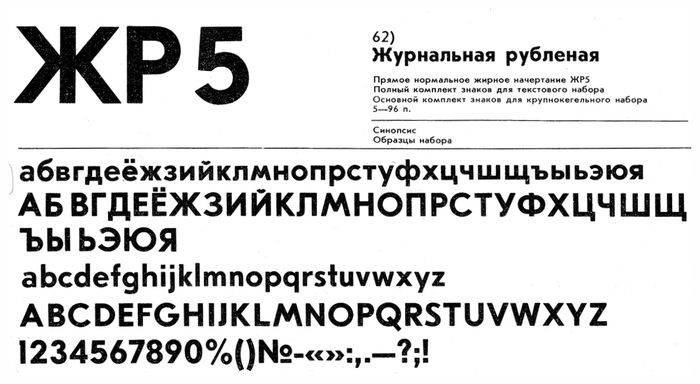
Какие выбрать шрифты для букваря и чем руководствоваться?
Сергей! Тут всё зависит от задачи и от вёрстки. На какой возраст рассчитан букварь? Как много текста будет на развороте? Какие будут иллюстрации? |
До сих пор существуют различные госты оформления детской литературы. В них, например, сказано, что антиквенные шрифты можно использовать только в литературе для детей от 11 лет. В букварях гост требует использования рубленых шрифтов, то есть без засечек. Эти стандарты существуют ещё с советских времён, и их целесообразность вызывает вопросы. Однако они до сих пор важны для некоторых издательств. Если от вас не требуют полного соответствия гостам, я бы не советовала опираться на них. Самый известный рубленый шрифт в советской детской литературе — гарнитура Букварная. Ей набирались буквари: Букварь. Просвещение, 1978 |
ОСТ 29.127-2002 оформления детской литературы |
На основе гарнитуры Букварной создан шрифт «Текстбук», а в 2008 году вышло обновление «Текстбук Нью». Несмотря на появление шрифтов-конкурентов, «Текстбук» не перестал быть популярен, и его до сих пор используют в детской литературе и не только. Например, Яндекс использовал этот шрифт для рекламных коммуникаций около пятнадцати лет. Самая узнаваемая фраза Яндекса, набранная этим шрифтом: Найдётся всё. Наружная реклама Яндекса, 2008 Я вижу главную проблему букварей не столько в выборе конкретного шрифта, сколько в общем облике книги. К сожалению, сейчас наиболее популярны такие буквари: Мария Манакова. Или даже такие: Марина Дружинина. Забавная азбука. Эксмо, 2011 Моя главная претензия к современным букварям, да и к детским книгам в целом, — это несоответствие шрифтов и характера книги. Помимо сомнительного качества иллюстраций и цветового безумия на разворотах, видно, насколько буквы не дружат с картинками. Я бы советовала выбирать шрифт исходя из того, как он будет смотреться вместе с иллюстрациями на листе. |
Вот хорошие примеры: Бруно Мунари. Азбука Бруно Мунари Для того, чтобы шрифт дружил с иллюстрациями, можно привести формы букв и формы иллюстраций к одному стилю. Контрастная антиква хорошо работает с иллюстрациями в азбуке Бруно Мунари.![]() Анна Кёвицеш. Венгерская азбука Ещё можно воспользоваться белым пространством листа и не нагружать разворот. В книге «Бубабу» потрясающие иллюстрации и выбран простой геометрический гротеск. Он не идёт вразрез с картинкой, стоит аккуратно и хорошо считывается.Концепт букваря «Бубабу» Компания «Грилли-Тайп» даже сделала шрифт «ГТ Еести» на основе эстонского букваря. Набирать сплошной текст им я бы не советовала, но в сочетании с яркими и простыми формами буквы выглядят хорошо: Шрифт «ГТ Еести» Мне кажется, самое прекрасное, что может быть в букварях и остальных детских книгах — взаимодействие с читателем. Оно есть, например, в объёмной попап-азбуке: Марион Батейль. Ещё пример взаимодействия с буквами в книге — это не букварь, но книга о типографике, рассчитанная на детей. Каждый разворот книги — это игра с буквами и интересные типографические задания: Студио 3. Гиперактивная типографика. Гештальтен, 2010 Антиквы или гротески, вёрстка строго по госту или нет — это всё, на мой взгляд, не самое важное. Важно, чтобы в итоге книгу хотелось рассматривать и взрослым, и малышам. |
Это не все типы шрифтов. Есть такие вариации, которые сильно разнятся от привычных нам. Они объединены в особые группы. КомпьютерныеГоворя о шрифтах, нельзя забывать и о компьютерных. Они представлены специальным файлом, который описывает буквенные, цифровые, служебные и псевдографические символы. Используется для визуализации этих знаков в программе или ОС. Сюда относятся и шрифты для Word. Дизайнеры часто употребляют слово «фонт», которое с английского переводится как шрифт, но именует конкретно компьютерную его версию. Может заменять название файла со шрифтом либо понятие «гарнитура». ТипологияВ этом случае типология несколько отличается от ранее описанной. Типы шрифтов могут различать по внутреннему устройству, ширине или применению. Если упоминают ширину символов, то различают моноширинные или пропорциональные шрифты. В первую группу относят символы с одинаковой шириной. То есть независимо от гарнитуры присутствует однозначность в размещении символов на дисплее. Помимо положительных черт, эта группа имеет и отрицательные характеристики. К примеру, наблюдаются проблемы с визуализации широких букв типа «Ш», заметна увеличенная ширина набора, а рисунок знака неравномерный. К пропорциональным относят символы с разной шириной. По применению выделяют три группы, в которых можно увидеть шрифты для Word. Есть моноширинные, без засечек и с ними. Каждый получил свое особое имя: Mono, Sans и Serif соответственно. Как уже говорилось ранее, типы эти есть в Word и подобных текстовых процессорах, также в веб-дизайне, графическом интерфейсе и т.д. Mono используют для визуализации исходного кода и чисел. С засечками символы лучше воспринимаются при чтении на высоких показателях DPI. Без засечек шрифт рекомендуют использовать для заголовка, важных пометок, текстовых фрагментов. К этому типу и относят «Гротеск». Компьютерные типы шрифтов относительно внутреннего устройства бывают растровые и векторные. Первый вариант представлен визуализацией символов с помощью пикселей, второй — математических формул. «Гротеск»Так мы подобрались к одному из типов шрифтов. Важно понимать, что вариантов «Гротеска» большое количество. Они получили популярность в 20 веке. Тогда их начали активно применять для привлечения внимания. Хотя иногда использовали и в текстовом наборе. Среди рубленых шрифтов известными стали «Готик», «Гельветика», «Универс». ИмяНазвание шрифта «Гротеск» предполагает много вариаций. Кстати, имя стиля может отличаться относительно местоположения. Так, в Англии и Франции шрифт будут именовать «Без засечек», в Америке вспоминать про «Готику», а в Германии упоминать «Гротеск». Поэтому если вы встречаете все эти названия, то важно понимать, что все они объединяют одни и те же стили. ПримерыИнтересно, что «Гротески» можно в свою очередь классифицировать и определить в несколько групп. Примеры шрифта гротеск можно увидеть в графическом или текстовом редакторе. Конечно, не все вариации доступны в стандартном наборе стилей. Но если вам понравился определенный тип, его легко найти и установить. Устаревшие «Гротески» известны с 1816 года. Отсюда и такое имя. Имеется небольшой контраст, он одноширинный, полузакрытый и открытый. Выглядит несколько грубо, поэтому и привлекает внимание. Часто тип относят к реализму. Новые «Гротески» стали продолжением развития старых и появились несколько позже. Стали немного изящнее, но отличительной черты в них не найти. Вариант перестал быть интересным для акцидентной продукции, поскольку стал похож на обыкновенный и незаметный стиль. Шрифт «Гротеск» из подгруппы геометрические соответствует своему названию. Символы заполучили геометрические формы, среди которых есть окружности, квадраты, равносторонние треугольники. ВыводыШрифт «Гротеск» непросто определить обычному пользователю. Он не всегда имеет что-то общее с видом художественной образности. Он считается современным, легким, нейтральным и функциональным. Сейчас его могут применять где угодно, поскольку он заполучил разнообразные подгруппы. Так его могут применять в деловой, технической или электронной документации. Иногда встречается в учебной литературе. Чаще всего заметен в интернете и цифровых технологиях. Несмотря на то, что стиль без засечек считается трудно читаемым, все зависит от применяемой подгруппы. На первый взгляд кажется, что за всю историю письменности придумано так много шрифтов, что разобраться в них просто невозможно. На самом деле все гораздо проще и все эти бесконечные вариации окружностей и палочек легко умещаются в стройную и простую систему. Все шрифты делятся на четыре большие группы, как времена года или стороны света:
АнтикваСтиль: академический, классический, традиционный, консервативный, элегантный. Если бы шрифты можно было бы сравнить с цивилизациями, антиква, несомненно, была бы представителем западной. Эти шрифты формальны, строги и имеют самую длинную историю. У них традиции и манеры. Особенность антиквы, как уже говорилось, засечки — накрахмаленные воротнички и манжеты букв, элементы, которые делают шрифт устойчивее, основательнее, аккуратнее. Антикве хорошо удается передавать смысл деловых документов, научных справочников и статей, больших объемных текстов. Бизнесмен с газетой скорее всего пробегает глазами антикву, студент, сдающий сессию, имеет дело с засечками. Антиква старого стиляСкругление засечек в местах примыкания к основному штриху и наклонная ось овальных элементов, умеренная контрастность. Переходная антикваРазница между основными и соединительными линиями в переходной антикве более явная, чем в старом стиле, но менее четкая, чем в антикве нового стиля. Антиква нового стиляОтличается более сильным контрастом между основными и соединительными линиями, строго вертикальными овалами, тонкими и длинными засечками. Брусковая антикваРазница между основными и соединительными линиями либо малозаметна, либо ее нет совсем, засечки мощные, прямоугольной формы. Как, например: ГротескСтиль: современный, легкий, нейтральный, функциональный. Это, несомненно, шрифтовой север — минималистичный, четкий, функциональный и прямолинейный, как шкаф из Ikea, не терпящий никаких излишеств, как например засечки антиквы или росчерки рукописных шрифтов. Эти элементы, как атавизм, исчезли за ненадобностью. Гротескные шрифты — это новая история, конструктивизм и Баухаус, космос и компьютеры. Лента Фейсбука — гротескный Gotham. Компании Microsoft, Panasonic и даже NASA. Старые гротескиПереходное звено в шрифтовой эволюции от антиквы до гротеска, буквы с небольшим контрастом. Примеры: Franklin Gothic, Akzidenze Grotesk Новые гротескиСамые нейтральные, одноширинные шрифты почти без контраста. Примеры: MS Sans Serif, Arial, Helvetica, Univers. Гуманистические гротескиИмеют большую контрастность в толщине штрихов. И гуманистическими они названы не случайно, а потому что напоминают рукописные (пером). Примеры: Gill Sans, Frutiger, Tahoma, Verdana, Optima, и Lucide Grande. Геометрические гротескиКак ясно из названия, строятся на основе геометрических форм. Пример: Futura, Geometria. Рукописные шрифтыСтиль: поэтический, художественный, декоративный. Применение: оформление приглашений, альбомов, изысканные заголовки, вывески, поздравительные открытки. Представьте себе сосредоточенного китайского мастера, выводящего пером иероглифы. Формальные рукописныеНеформальные рукописныеНе такие старомодные как формальные и в принципе, похожи на большинство почерков современного человека, не обладающего каллиграфическим навыком. Примеры: Mistral и Brush. Акциндентные шрифтыСтиль: декоративный, народный, фантазийный. Это все странные, стилизованные, художественные, дизайнерские и слегка ненормальные шрифты. Читать с их помощью большие объемы текста – получится едва ли. Также называются рубленые шрифты, Grotesk (в Германии), Grotesque (в Англии и Франции), Gothic (в Америке). Впервые наборные шрифты без засечек появились в начале XIX века в Англии, хотя подобная форма знаков применялась еще в надписях античной Греции. Вначале применялись исключительно как акцидентные, но в ХХ веке стали использоваться для набора текста. Характеризуются, как правило, малой контрастностью или полным отсутствием визуального контраста между основными и соединительными штрихами. В соответствии с формой овалов, наличием или отсутствием контраста, степенью открытости знаков и степенью разноширинности гротески делятся на старые, новые, геометрические и гуманистические. Старые гротескиПервый гротеск появился в 1816 году в Англии. Это шрифты с небольшим контрастом, одноширинные, полузакрытые и открытые. Знаки имеют простую и даже грубую геометрическую форму, с крупным очком строчных. Шрифты в целом оставляют впечатление сурового грубого реализма. В некоторых шрифтах только прямые начертания, в других имеются наклонные (не курсивные). Угол наклона знаков средний. Новые гротески развивают принципы построения старых гротесков. Они появились в 50-х годах ХХ века и были вызваны к жизни потребностями функциональной швейцарской школы типографики. Новые гротески гораздо изящнее своих предшественников и почти не имеют отличительных черт, что позволяет характеризовать эти шрифты как стандартные и незаметные. Это закрытые одноширинные шрифты почти без контраста, с крупным очком строчных знаков, сильно развитые по начертаниям. Открытые гротескиСамый новый и самый современный тип гротесков. Общая черта
Механистические гротески
Антиква-гротескиАкцидентные и текстовые шрифты, по форме промежуточные между гротеском и антиквой. Имеют на концах штрихов либо едва заметные утолщения, либо маленькие острые засечки. Геометрические гротески принципиально строятся на основе простейших геометрических форм – окружности, квадрата, равностороннего треугольника. Эти шрифты появились в 30-е годы ХХ века в Германии под воздействием идей конструктивизма и школы дизайна Баухауз. А, м. grotesque, нем. Grotesk <ит. grotesca. 1. иск. Изображение, отличающееся причудливым, фантастическим сочетанием мотивов и деталей. Сл. 18. Картина, живописная вещь из многих красок и худых фигур. ЛВ 1 2 63. Украшение комнат составляют… … Исторический словарь галлицизмов русского языка Гротеск (фр. grotesque, буквально причудливый, комичный; итал. grottesco причудливый, итал. grotta грот, пещера): Гротеск вид художественной образности; орнамент, в котором причудливо, фантастически сочетаются… … Википедия Гротеск, вид типографского шрифта с равномерной толщиной штрихов, без отсечек. Полуустав Цифры и русские буквы в стиле готического шрифта Шрифт (нем. … Википедия — [тэ], а; м. [итал. grotesca] 1. Художественный приём в искусстве, основанный на чрезмерном преувеличении, сочетании неожиданных, резких контрастов; изображение чего л. в фантастическом, уродливо комическом виде. Мастер гротеска. Г. в литературе.… … Энциклопедический словарь Шрифт — (от нем. Schrift «письмо») – графическая форма определенной системы письма, в которой изображение букв и других письменных знаков имеет общую закономерность построения и единый стиль. Все шрифты классифицируются и систематизируются по группам,… … Грамматологический словарь I м. 1. Художественный приём в искусстве, основанный на чрезмерном преувеличении, нарушении границ правдоподобия, сочетании резких, неожиданных контрастов. 2. Произведение литературы и искусства, созданное на основе такого приёма. гротеск — (тэ/) а; м. (итал. grotesca) см. тж. гротескный, гротесковый, гротескно, гротесково 1) а) Художественный приём в искусстве, основанный на чрезмерном преувеличении, сочетании неожиданных, резких контрастов; изображение чего л. в фантастическом,… … Словарь многих выражений Гротеск (шрифт без засечек) и антиква (шрифт с засечками) Рубл … Википедия Книги